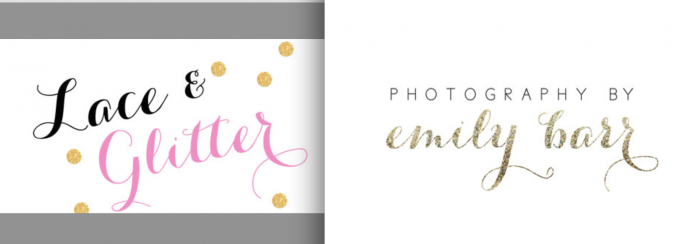
Wer kennt diesen Font?
Ich suche diesen Font, der derzeit auf zahlreichen Weddings Inivitations usw sein verschnörkeltes Unwesen treibt.
Wer kennt diese Schrift und kann mir sagen, wie sie heißt?